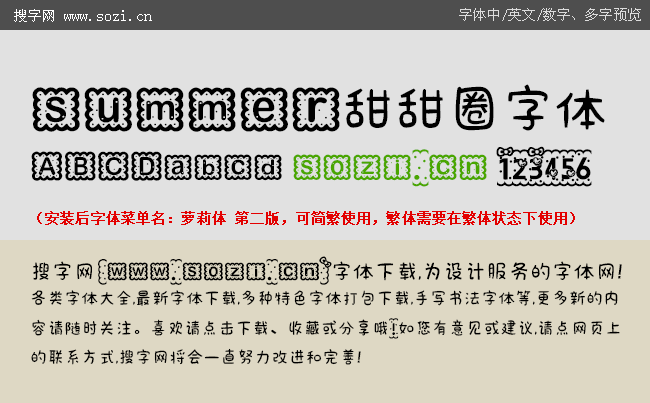
summer甜甜圈字體
搜字網(wǎng)給大家提供一款很卡通的手機(jī)中文字體下載。修改者給這款字體叫summer甜甜圈字體,這款手機(jī)中文字體以POP字體為原形,為字體標(biāo)點(diǎn)和英文加上了可愛(ài)的卡通外框,真的是非常有趣又可愛(ài)的一款字體,非常適合喜歡卡通的朋友在手機(jī)上安裝使用。